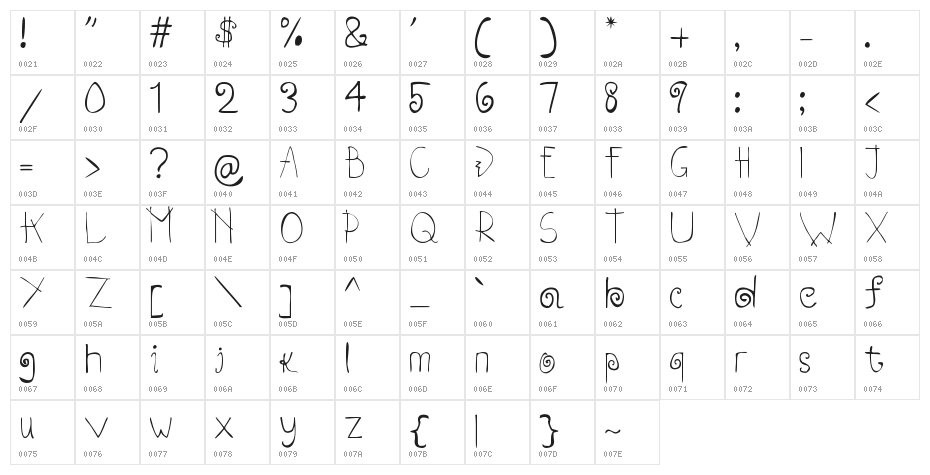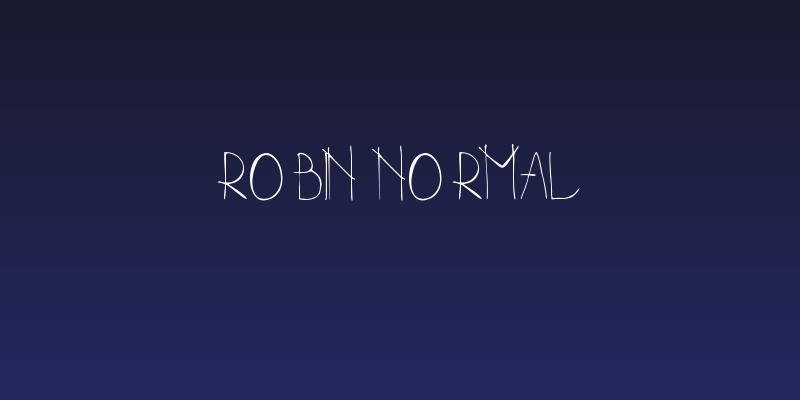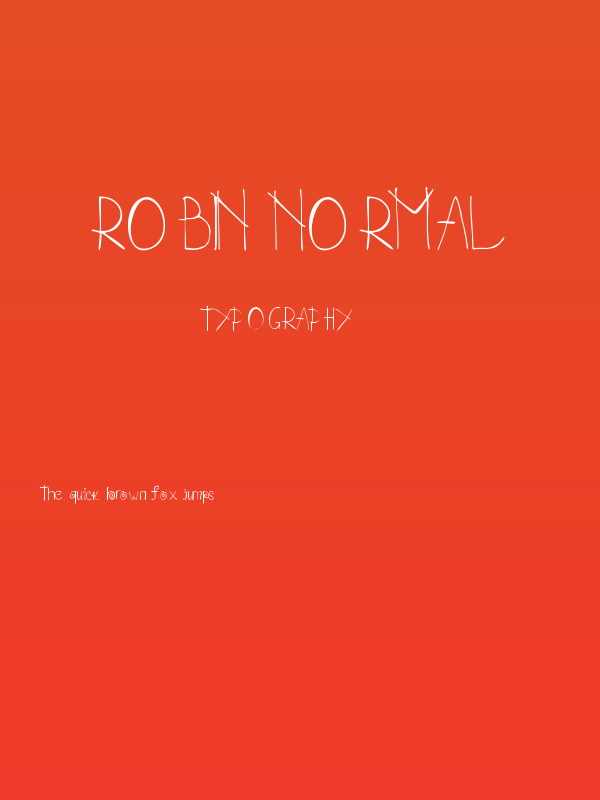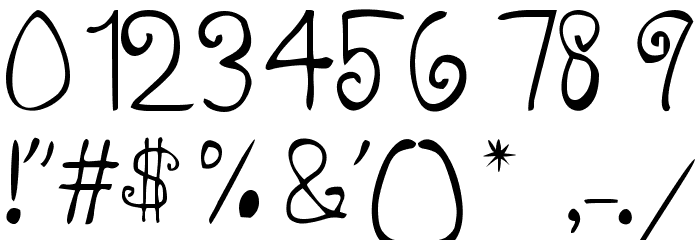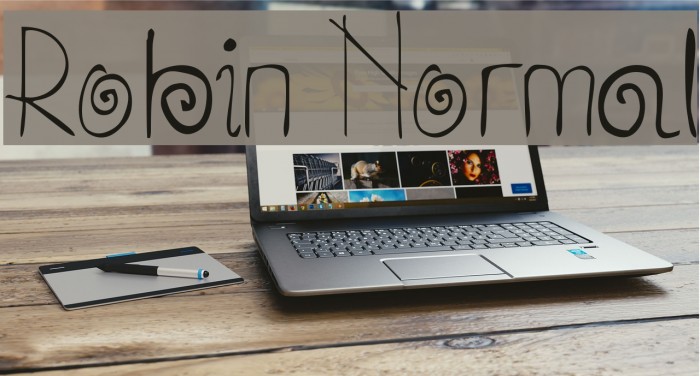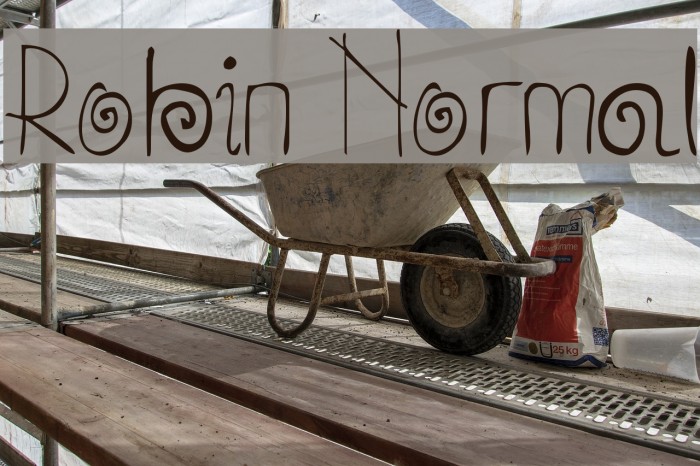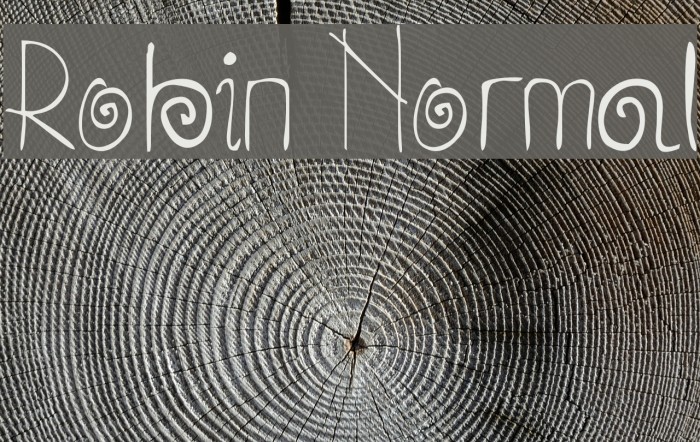
Robin Normal Font
| Stil general | Whimsical, Playful, Hand-drawn |
| Proiecte propuse | Ideal for children's books, playful branding, creative posters, and informal invitations. |